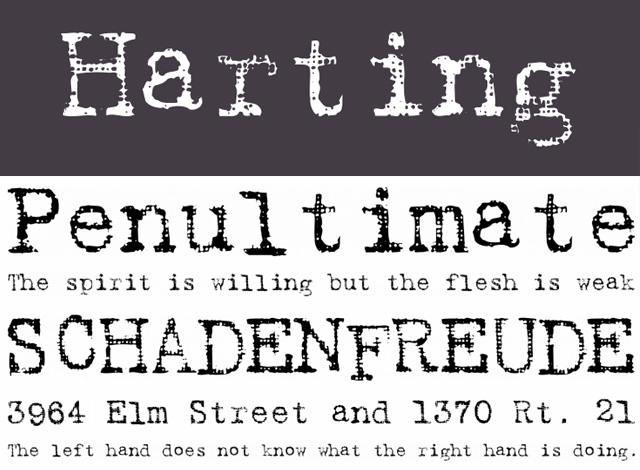
Этот самый запоминающийся из бесплатных шрифтов для пишущих машинок отлично использует пустое пространство, поэтому он должен работать на любом выбранном вами цвете фона.
Создатель объясняет, что «для спасения лишнего» они создали цифровой компьютерный шрифт.